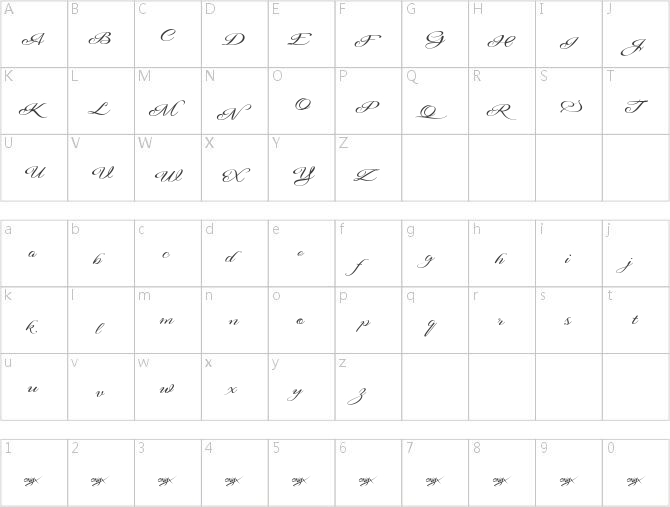
Signarita Anne 詳情頁(yè)
Signarita Anne字體字庫(kù)是一款讓人賞心悅目、百看不厭的英文字體,適合各類(lèi)廣告和產(chǎn)品包裝設(shè)計(jì)應(yīng)用,字體大小0.03MB,格式為ttf字體,上傳用戶(hù)是手機(jī)洗相,作者/版權(quán)方為未知